WORKSHOP Ilustração Tipográfica com Ana Biscaia
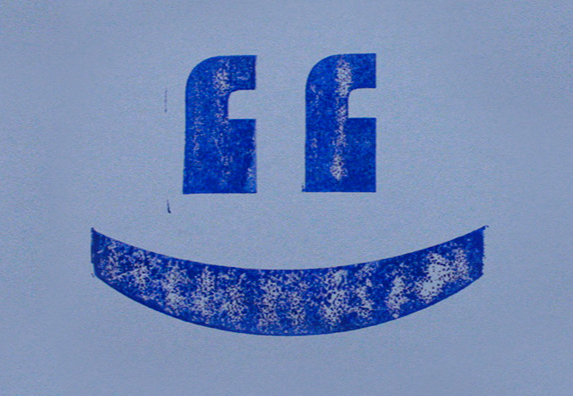
Este workshop será dado pela ilustradora Ana Biscaia, com o auxílio do Clube dos Tipos. Utilizando letras, padrões e elementos tipográficos decorativos, iremos criar imagens. Neste workshop vamos tirar partido de técnicas tradicionais da oficina de tipografia, mas incluímos métodos mais experimentais que permitem chegar a resultados mais livres, no intuito de criar impressões únicas.
Ana Maria Biscaia (n.1978). Ilustradora e Designer gráfica. Estudou design de comunicação na Universidade de Aveiro. Tirou um mestrado em Illustration and Graphic Design na Konstfack University College of Arts, Crafts and Design em Estocolmo. Ganhou o Prémio Nacional de Ilustração 2013 com o livro “A cadeira que queria ser sofá.” de Clovis Levi (editado pela Lápis de Memórias). Colabora em projectos colectivos de ilustração e banda desenhada.